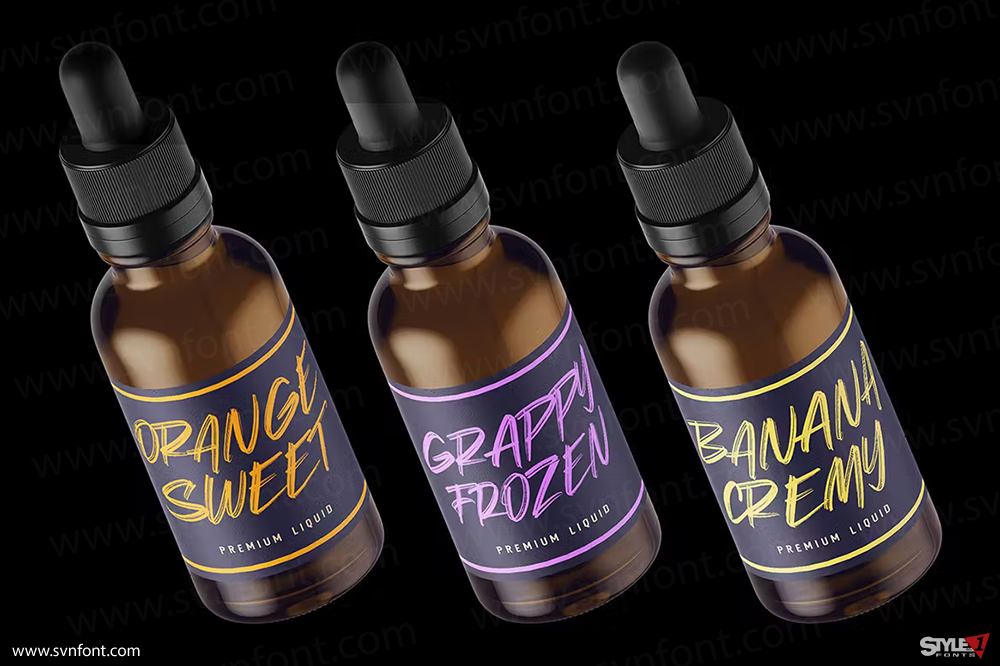
Break Herd là một phông chữ hiển thị hoàn toàn mới. Sự lựa chọn hoàn hảo cho những tấm áp phích bắt mắt hoặc các bài thuyết trình sản phẩm độc đáo. Hãy sử dụng trí tưởng tượng của bạn và tạo ra những dự án mới tuyệt vời với phông chữ này.